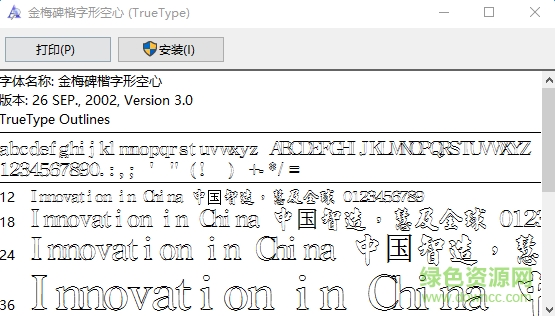
金梅碑楷字形空心字體是一款很有特色的電腦空心字體,這款字體不像普通的字體那樣是實心的,它寫出來的字是空心的,而且很美觀、大氣,讓人看著都很舒服,喜歡的朋友可以來綠色資源網(wǎng)下載。
金梅碑楷字形空心字體是真的很不錯的,可以用于藝術(shù)設(shè)計或者是廣告設(shè)計,而且字形大方、美觀,歡迎大家來綠色資源網(wǎng)下載使用。